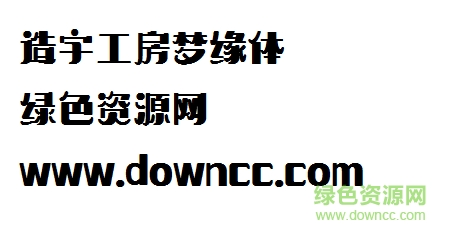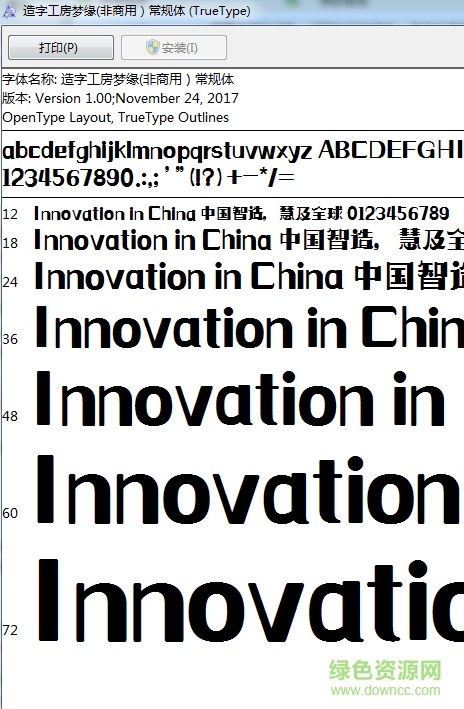
造字工房夢(mèng)緣體字體
造字工房夢(mèng)緣體是一款唯美漂移的中文字體軟件,字體筆畫橫細(xì)豎粗,頗有一種毛筆字體的風(fēng)范,非常有創(chuàng)意,覺得好看的朋友就到本站下載使用吧!
造字工房夢(mèng)緣體字體優(yōu)美清新,線條流暢,給人以華麗柔美之感,此種類型的字體,適用于女用化妝品、飾品、日常生活用品、服務(wù)業(yè)等主題。
關(guān)于造字工房
造字工房創(chuàng)立于二零零九年年初,專注于漢字新字體字形設(shè)計(jì)與開發(fā)。整個(gè)設(shè)計(jì)團(tuán)隊(duì)由從事多年商業(yè)設(shè)計(jì)的平面設(shè)計(jì)師和專業(yè)字體設(shè)計(jì)師組成,我們對(duì)漢字持有深厚的感情,多年來一直致力于漢字字體字形的設(shè)計(jì)、應(yīng)用和研究。